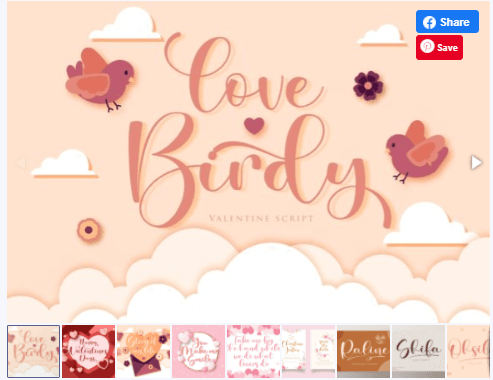
Love Birdy Font
Love Birdy - восхитительный рукописный шрифт. Этот адаптируемый скриптовый шрифт имеет широкий спектр применений, от поздравительных открыток до заголовков, и гарантированно добавит мечтательности вашему следующему проекту.